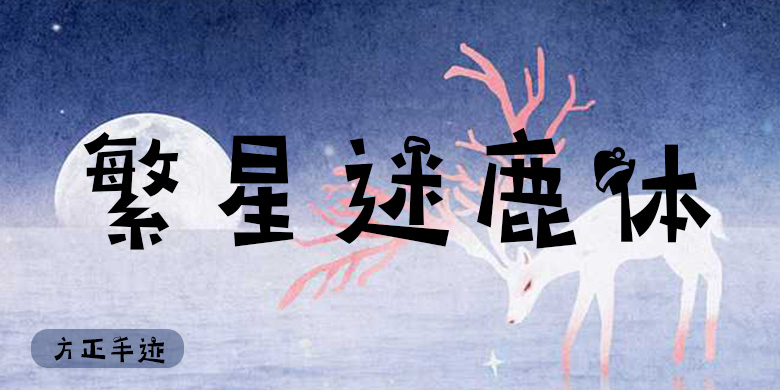
方正手迹-繁星迷鹿体
字体品牌: 方正手迹 设计师:李潇,高宇 字体分类:创意书写 字体属性:精品字 字符集:大陆简体(GB2312-80) 发布时间: 2020
这款字是一款圣诞主题的字体,主体字自带旋律和舞蹈,圣诞元素做成挂件很好地融入到字体当中。适用于现代诗歌、短文的排版,以及屏显、影视综艺,及文化、商业类品牌的广告语设计。